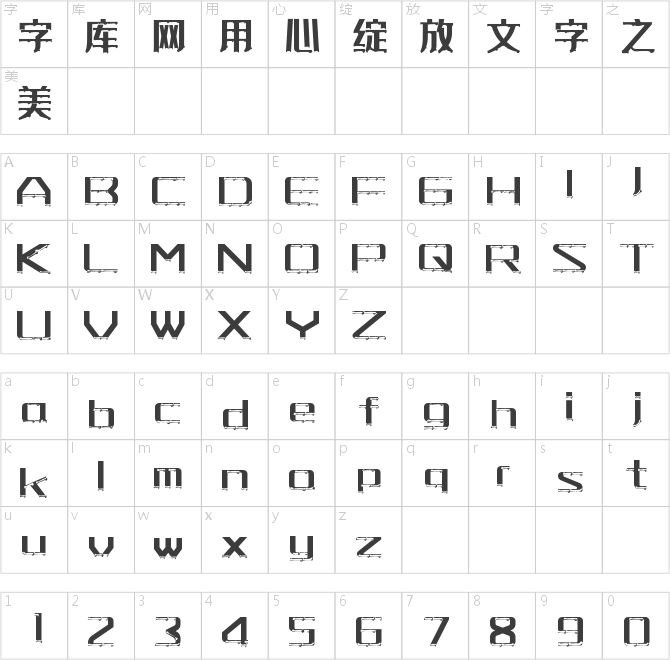
字魂247号-经典雅黑(漆版) 详情页
字魂247号-经典雅黑(漆版)
字魂247号-经典雅黑(漆版)字体zihun247hao-jingdianyahei(qiban)字库是一款让人赏心悦目、百看不厌的中文字体,适合各类广告和产品包装设计应用,字体大小9.97MB,格式为ttf字体,上传用户是徐明泽,作者/版权方为字魂字库